فونت دستنویس انگلیسی زیبا
فونت دستنویس انگلیسی زیبا که در این مطلب شاهد آن هستید مجموعهای کمنظیر از فونتهای دستنویس با طرحهای گلدار و فوقالعاده زیبا هستند که مناسب جهت استفاده در طراحی و گرافیک به خصوص طراحی انواع کارت تبریک و کارت عروسی میباشند. این مجموعه شامل 10 قلم انگلیسی است که در قالب فایلهای ttf, otf, woff, woff2 بر روی سایت بارگذاری شدهاند که با نصب فایلهای otf یا ttf در پوشه فونتهای سیستم، میتوانید از آنها در طرح و پروژههای گرافیکی خود استفاده کنید. از این مجموعه میتوان در طراحی انواع کارت تبریک، کارت پستال، کارت عروسی، طراحی انواع پوستر، قاب عکس، طراحی بر روی بستهبندی محصولات، طراحی ظروف سلولزی و کاغذی، طراحی بر روی تیشرت، طراحی قاب و کاور موبایل، طراحی کارت ویزیت، بروشور، تراکت، بنر و دیگر پروژههای گرافیکی استفاده نمود. همچنین اگر طراح صفحات وب هستید میتوانید از نسخههای woff فونتها در طراحی سایت نیز استفاده کنید.
پیش نمایش و نام فونتهای دستنویس موجود در این مجموعه
فونت Forgotten Melody
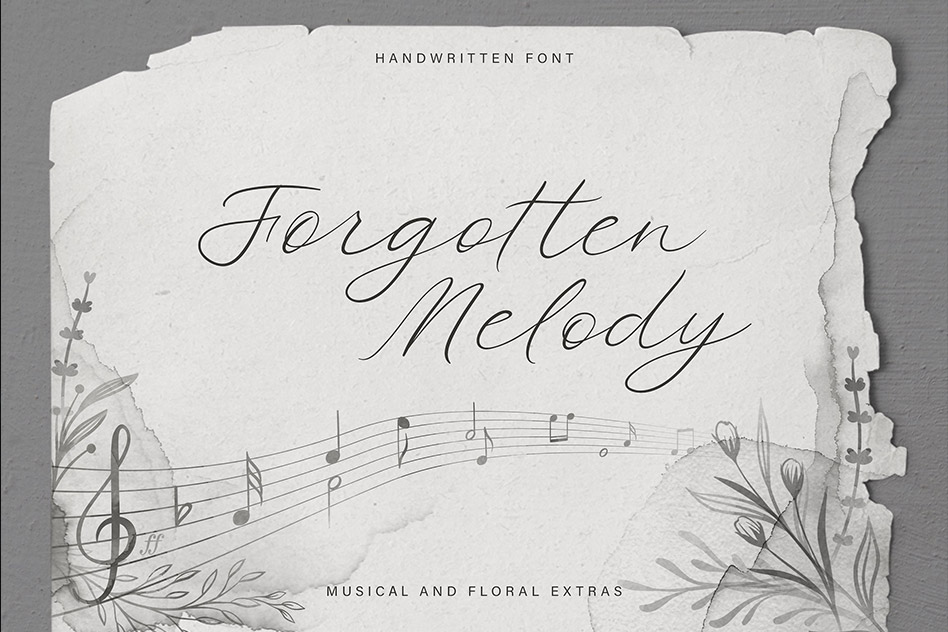
فونت Herbarium
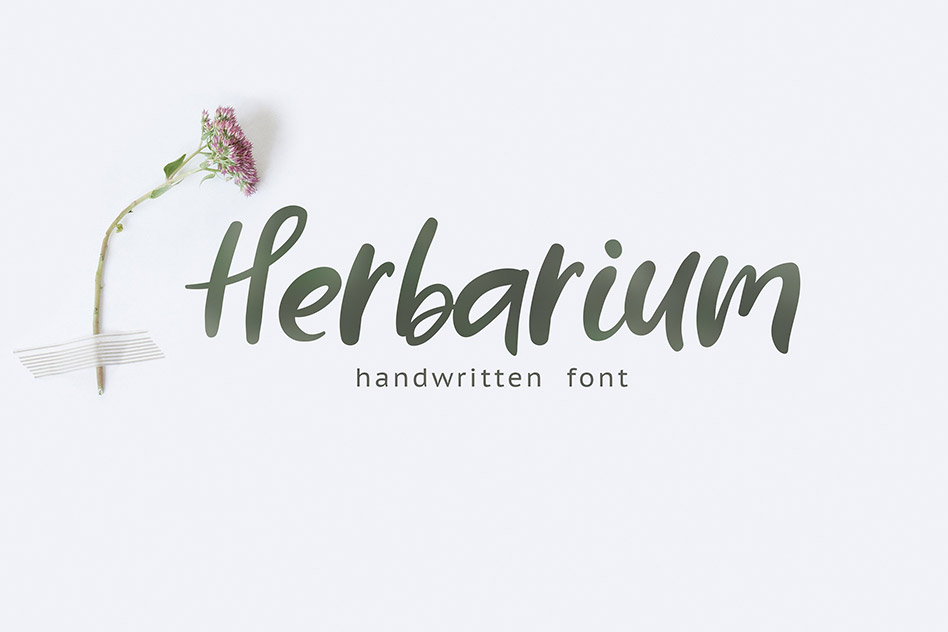
فونت Jubilation
فونت LeJardin
فونت Limerence
فونت MagicIvy
فونت Millennials
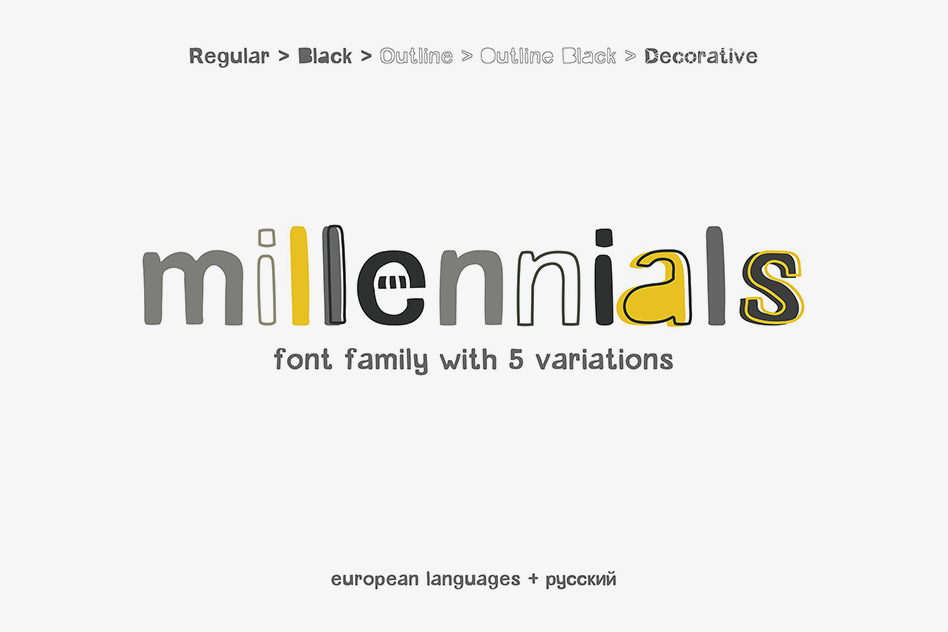
فونت Odour
فونت Quaint Garden
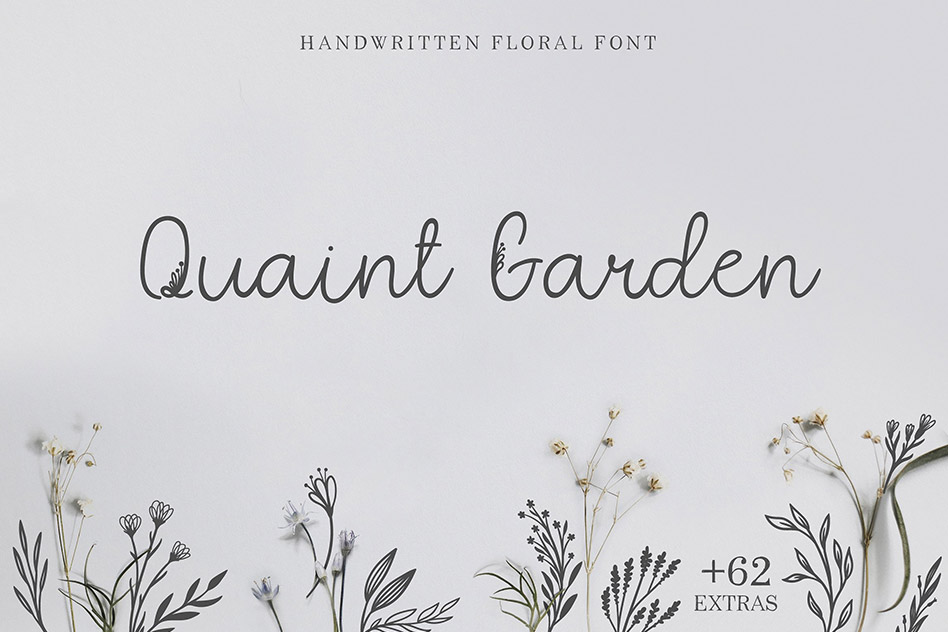
فونت Seascape